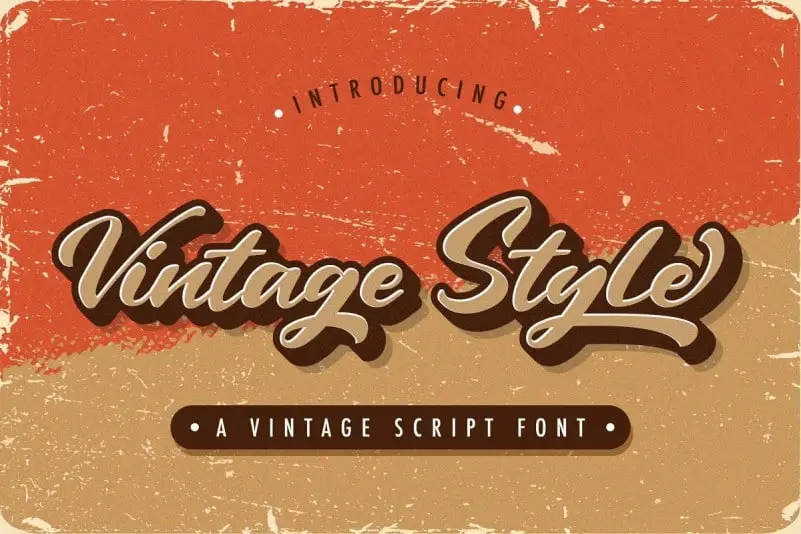
A Vintage Style Script Font é uma escolha perfeita para quem busca dar vida às suas ideias criativas com estilo elegante e vintage. Feita pelo designer StringLabs, essa fonte traz a sofisticação de um script antigo, mas também sua versatilidade e facilidade de uso. Curvada e arredondada, ela adquire o toque especial de um design vintage que torna cada palavra uma obra de arte em seu próprio direito. Perfeita para aplicar nos seus logotipos ou em qualquer projeto de marca que deseje destacar-se, esta fonte invita a experimentar as possibilidades criativas que ela pode oferecer. Adicione-a à sua biblioteca e inspire-se com o poder transformador de uma excelente fonte vintage elegante.